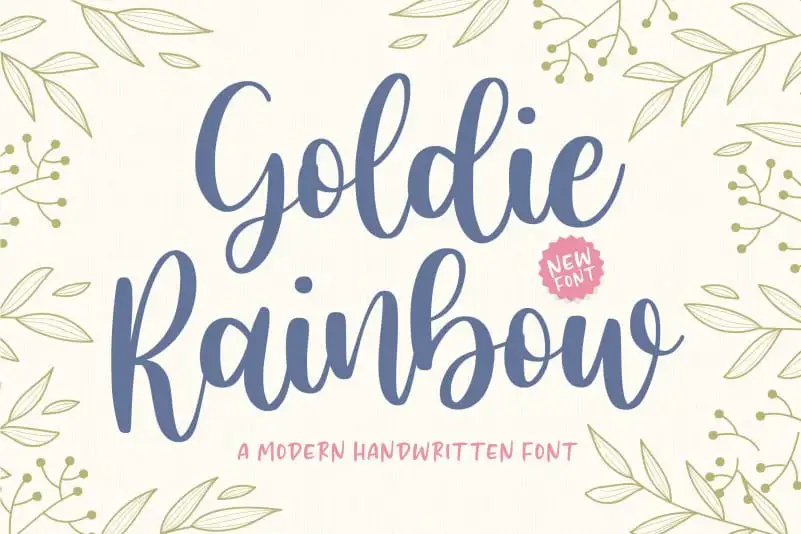
Goldie Rainbow Handwritten Font – Download Grátis
A fonte ‘Goldie Rainbow Handwritten’ é ideal para projetos que precisam de uma autenticidade natural e envolvente. Seja para aplicar em embalagens de produtos, criação de marca, revistas, mídias sociais, casamentos ou apenas como um toque criativo sobre o fundo. Esta fonte possui traços fluidos e alegres que transmitem sentimentos de felicidade e entusiasmo, tornando-a perfeita para expressar ideias em uma variedade de cenários. A ‘Goldie Rainbow Handwritten’ é uma escolha ótima para quem busca um equilíbrio entre originalidade e elegância em seu design visual.